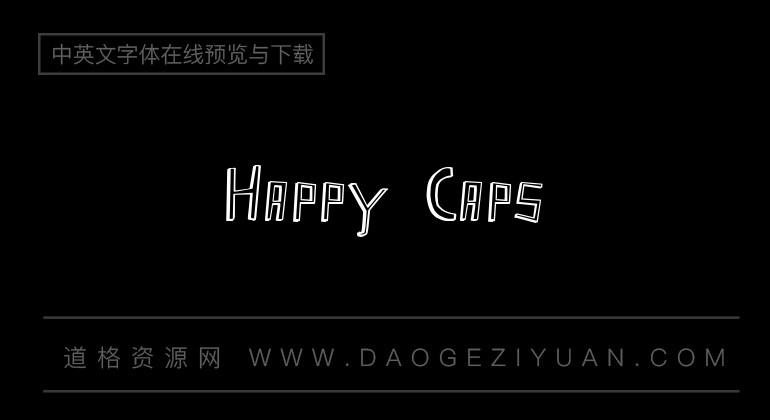
Happy Caps
? Happy Caps 是一款由英国设计师Luke Lisi设计的字体,它具有独特的外观,可以帮助设计师创造出令人惊叹的设计作品。Happy Caps字体采用了粗细混合的设计,具有简洁、活泼、有趣的外观,可以给设计师带来无限的创意灵感。它还拥有完整的Unicode支持,可以用于支持任何语言的设计。
Happy Caps是一款非常不错的手写艺术字体,具有很好的视觉感,适合于文化类的宣传设计、商业类品牌的广告和产品包装设计以及个性化文字排版等较多场景。